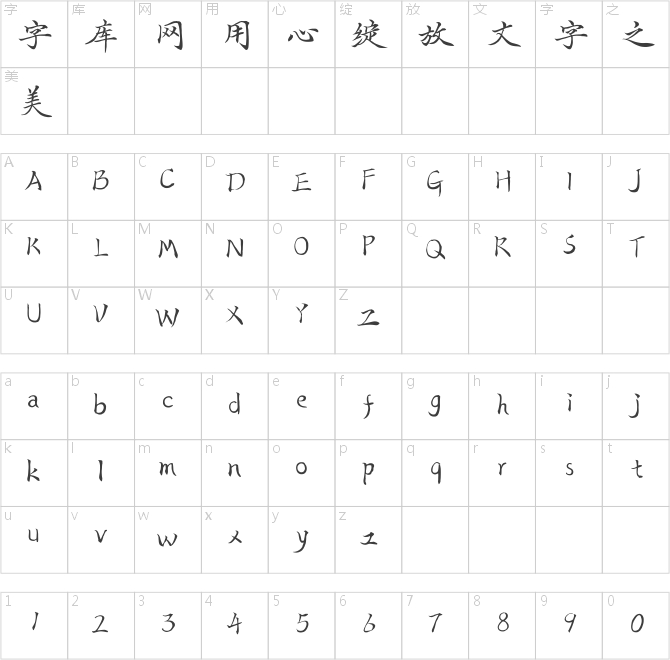
字体名称: 汉仪常江小楷
汉仪常江小楷
汉仪常江小楷介绍
作者介绍
“汉仪常江小楷” 是由西安书法家协会会员、汉仪签约字体设计师常江所书写创作的一款书法字体。常江不仅擅长书法,还是一位资深媒体人,他是微博2019十大影响力书法博主,曾获得微博首届手写大赛冠军。他的书法传播范围广,在微博、小红书、抖音、B站等各大社交平台上都非常受欢迎。
“汉仪常江小楷” 充分还原了书法作品的字形特点,细节表现十分完整。可广泛用于海报、品牌和媒体等宣传方面的使用。
笔势灵秀飞动
“汉仪常江小楷” 的整体态势均向右上方倾斜,字形气势整齐统一,增强了其排版效果的节奏感。
结构劲健洒脱
“汉仪常江小楷” 灵秀飞动,不同汉字结构的字面差异较大。从间架结构来讲主要有三种情况:上展下收、上收下展和中间伸展。虽然是楷书,却有着行书的行气畅达、富于变化,遒美妍丽中透出劲健挺拔。
“汉仪常江小楷” 风格飘逸,字体内收外放,外部笔画舒朗。以“更”、“皮”和“我”为例,中宫较为紧密,撇捺略显张扬。
笔画俊秀而不失张力
“汉仪常江小楷” 的线条流畅有弹性,笔画遒劲俊雅富有张力,字体空间浑圆饱满,展现出了卓尔不凡的气势。
“汉仪常江小楷” 在部分笔画衔接处有留白,给予了字体与众不同的透气感和呼吸感。这使字体气息更加流畅,更加具有生命力。
中西文匹配
“汉仪常江小楷” 的西文同样用毛笔书写,融入了中文书法的手写方式。笔触丰富,运笔流畅,手写感强,中西文的搭配和谐统一。
排版效果
“汉仪常江小楷” 有着中宫收紧、笔画舒展的字体特点,因此在竖排时会有更好的展示效果。字体的风格古典雅致,适用于诗歌、书信短文的排版,以及文化、商业类品牌的宣传包装设计。